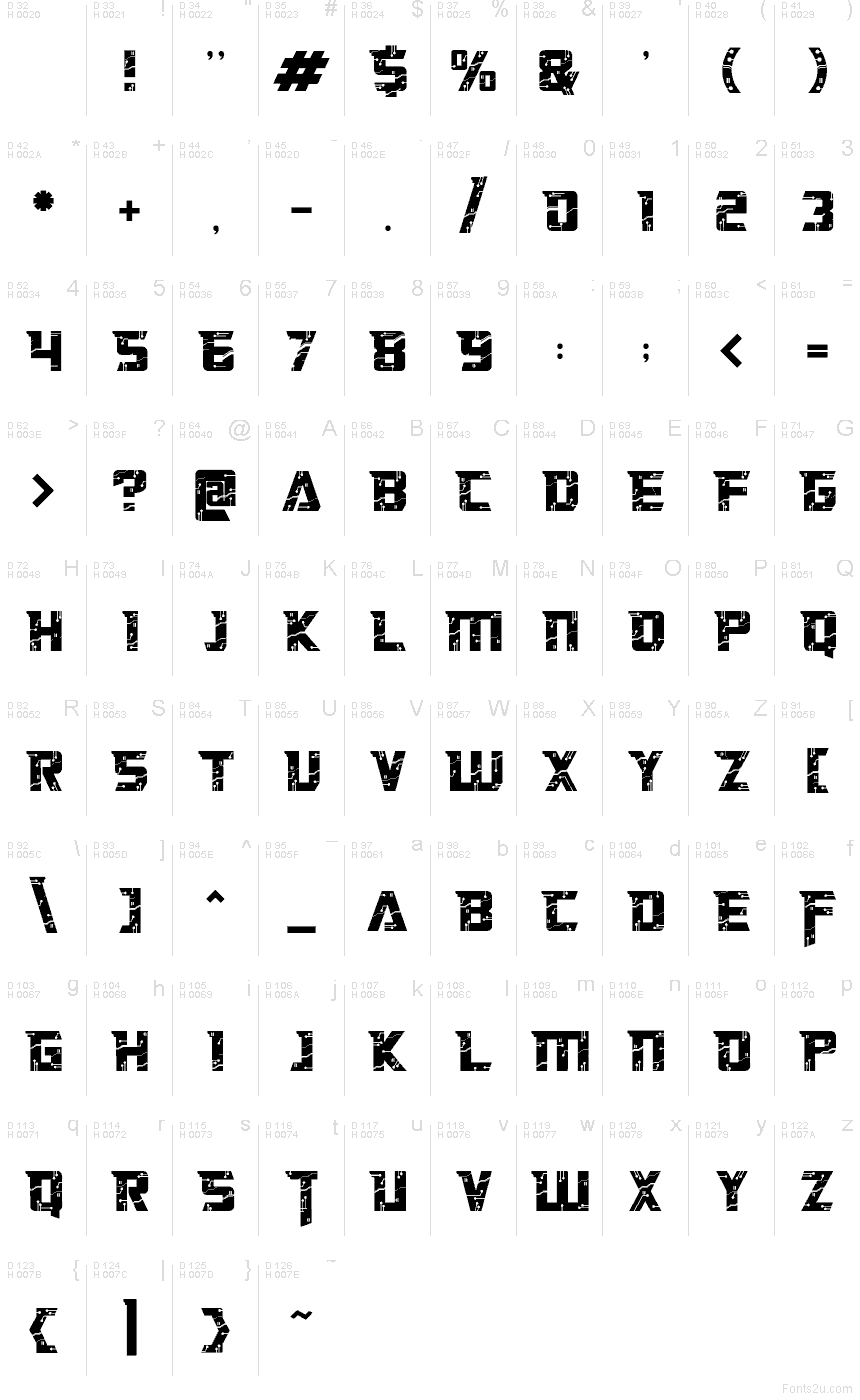
Turbo Type Two od Putracetol Studio je bezplatné písmo typu display inspirované plošnými spoji, které mění každé písmeno v panel plný drah, bodů a drobných propojení. Tento opakující se elektronický motiv dodává designu schematickou texturu, takže písmo nepůsobí jen jako běžný technický styl, ale jako označení vyříznuté z desky plošných spojů (PCB).
Nejlépe se hodí pro herní tituly, plakáty na technologické akce, úvodní obrazovky aplikací, grafiku pro streamy a obaly ve sci-fi stylu, kde tato estetika obvodů pomáhá vyprávět příběh. Nejvíce vynikne v krátkých nadpisech a logotypech, protože vnitřní vzor dodává i jednoduchým slovům hustý, inženýrsky zpracovaný povrch.
Turbo Type Two